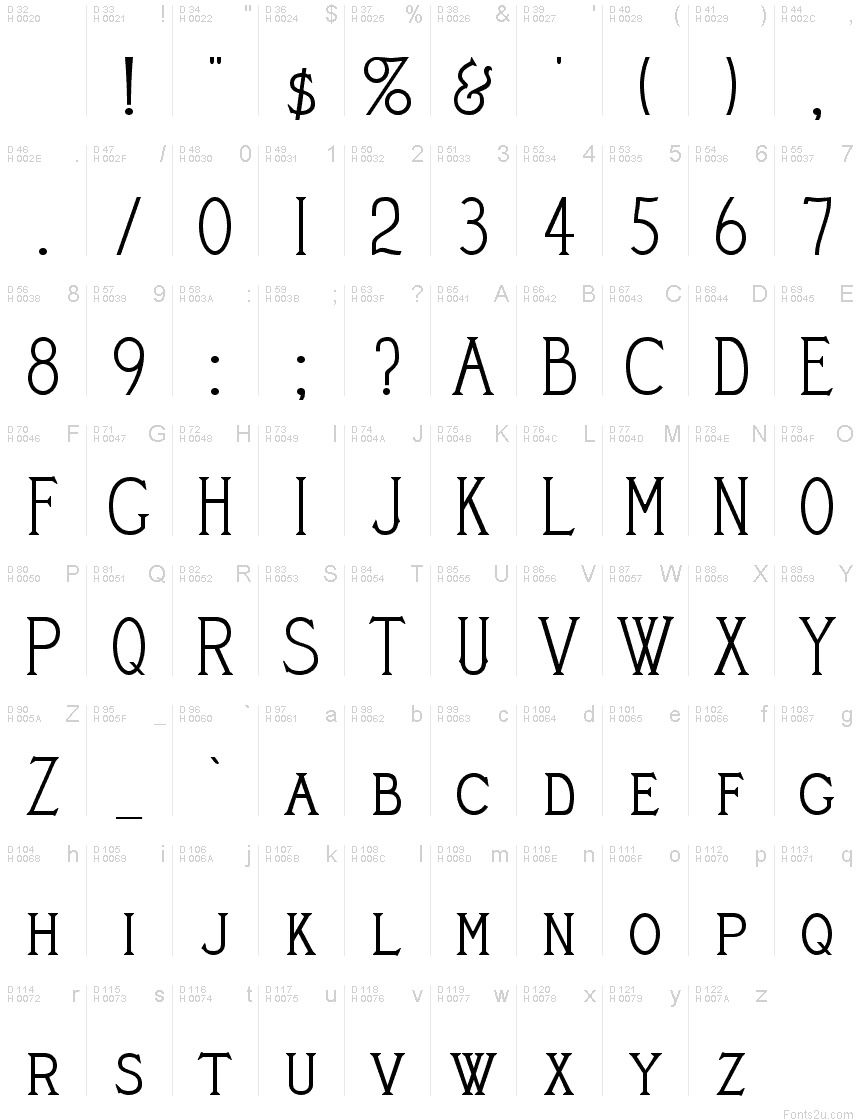
Cleaver's Juvenia to bezpłatny krój szeryfowy o wysokiej, smukłej sylwetce i subtelnie dramatycznym charakterze. Litery są wąskie i wyprostowane, z cienkimi, przypominającymi tusz liniami oraz ostrymi, wyraźnymi szeryfami, które sprawiają wrażenie antycznych, nie wpadając przy tym w parodię. Czcionka ta ma elegancję tytułu starej książki, ale z lekko niepokojącą ostrością, która przyciąga wzrok.
Dzięki Cleaver's Juvenia nagłówki zyskują literacki, niemal okultystyczny klimat, który świetnie sprawdza się na okładkach książek, przy otwarciach rozdziałów, na plakatach w stylu vintage, w brandingu fantasy lub kryminałów, a także na zaproszeniach i nastrojowych menu. Ten darmowy font najlepiej prezentuje się w dużych rozmiarach, gdzie jego smukłe detale mogą w pełni wybrzmieć. W przypadku tekstu głównego warto połączyć go z czystym, dyskretnym krojem bezszeryfowym, aby zachować czytelność i wyrafinowanie projektu.